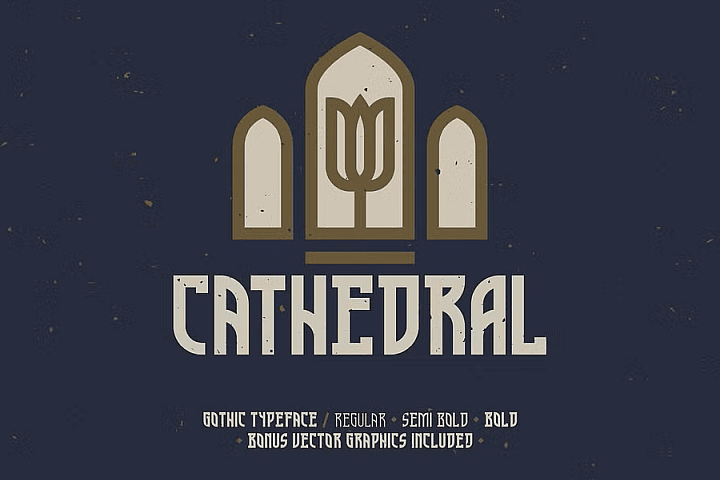
Cathedral
モダンなようでレトロなようなディスプレイ。直線と 1/4 円弧を組み合わせて形作られた面白い書体で、コンデンスで太めなためか、全体的になぜかゴシック(ブラックレター)の雰囲気を持っている。字によって大きめのスラブセリフが付いてたり付いてなかったりだからだが、不思議と不揃いな感じはしない。3ウェイトあって、細い方はこれまたなぜかルーン文字のような雰囲気を醸し出す。ロールプレイングゲームなどに似合いそうな書体。名前は「大聖堂」とかそんな意味。大文字のみ。